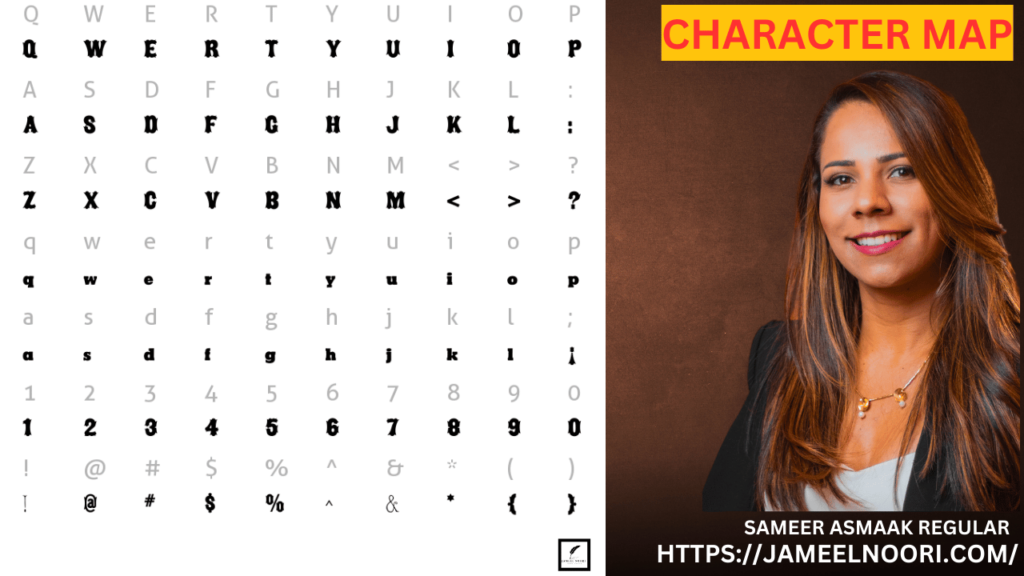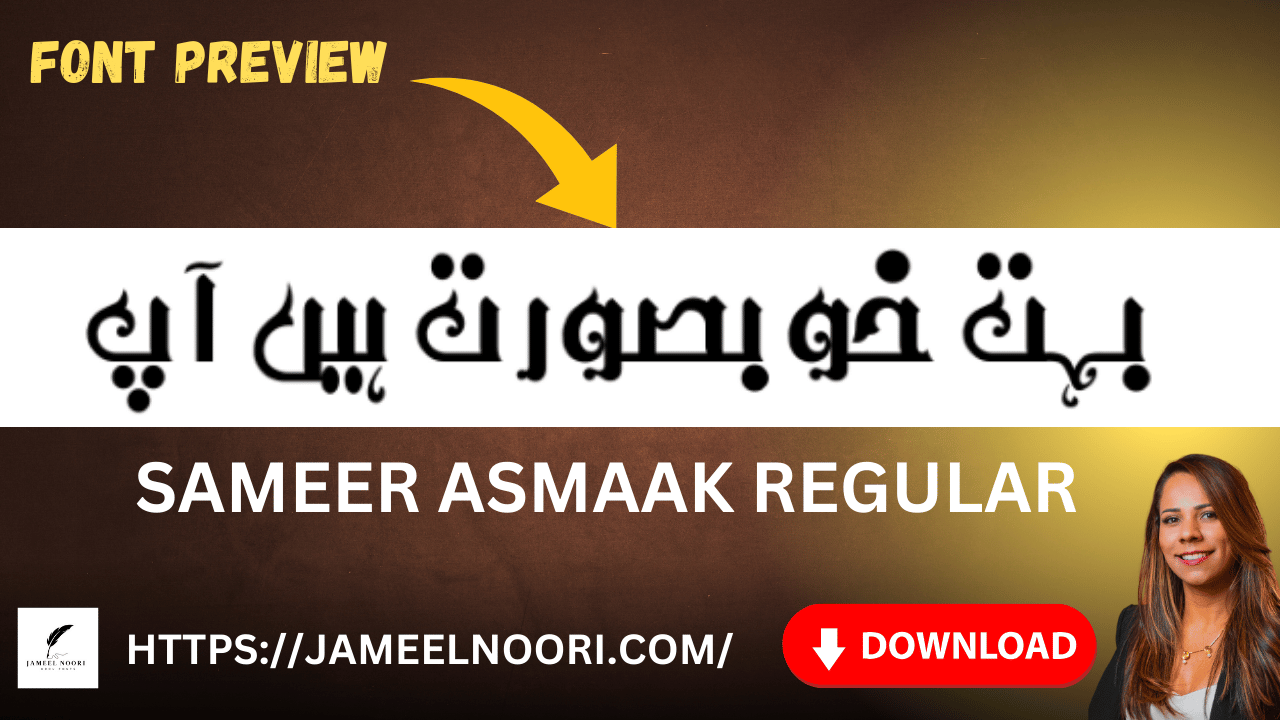
Sameer Asmaak Regular download urdu font by Jameel Noori aik stylish aur readable Urdu font hai jo modern aur traditional dono design needs ke liye perfect choice ban chuka hai. Yeh font specially un users ke liye banaya gaya hai jo Urdu fonts, Arabic fonts, aur best Arabic font ki search me rehte hain aur chahte hain ke unka content professional aur elegant lage. Is article me hum apko is font ke bare me complete information dy gy taki aap bina time waste kiye is font ka best use kar saken.
What is Sameer Asmaak Regular Download Urdu Font by Jameel Noori?
Sameer Asmaak Regular urdu font by Jameel Noori aik TrueType Font (TTF) hai jo Urdu typography ko smooth aur readable banata hai. Yeh font specially blogs, Islamic content, poetry, aur graphic design projects ke liye design kiya gaya hai. Pakistan, Lahore, Karachi aur worldwide users ke liye yeh font aik reliable choice mana jata hai.
Is font ki popularity ka reason iska clean structure aur balanced letter spacing hai jo long Urdu text ko bhi easily readable bana deta hai.
Key Features of Sameer Asmaak Regular Download Urdu Font by Jameel Noori
Sameer Asmaak Regular urdu font by Jameel Noori kai powerful features ke sath aata hai jo isay dusray Urdu fonts se different banate hain:
- Professional aur clean Urdu letter style
- Web aur print dono ke liye suitable
Yeh features isay expert choice Urdu font banate hain jo beginners aur professionals dono use kar sakte hain.
Where Can You Use Sameer Asmaak Regular Urdu Font by Jameel Noori?
Sameer Asmaak Regular download urdu font by Jameel Noori multiple use cases ke liye ideal hai, jaise:
- Urdu blogs aur news websites
- Islamic posts aur Quranic content
- Social media Urdu designs
- Poetry aur Shayari posters
- Print media aur banners
Why Sameer Asmaak Regular Download Urdu Font by Jameel Noori is Best Choice?
Sameer Asmaak Regular download urdu font by Jameel Noori is liye best mana jata hai kyunki yeh readability aur beauty ka perfect combination hai. Dusre fonts ke muqable me yeh font low-end systems par bhi smoothly work karta hai.
Lahore aur Karachi ke graphic designers ke darmiyan yeh font fast popularity hasil kar raha hai kyunki yeh professional output deta hai.
Is font ka use aap ko ultimate Urdu typography experience deta hai jo globally appreciated hai.
Conclusion – Sameer Asmaak Regular Download Urdu Font by Jameel Noori
Sameer Asmaak Regular download urdu font by Jameel Noori aik complete aur reliable Urdu font hai jo free availability, clean design aur easy installation ki wajah se users ki first choice ban chuka hai. Agar aap best Arabic font ya professional Urdu fonts ki talash me hain to yeh font aap ke liye perfect option hai.
Yes, it offers excellent readability for long Urdu content.
Yes, it supports Urdu and Arabic script styles.